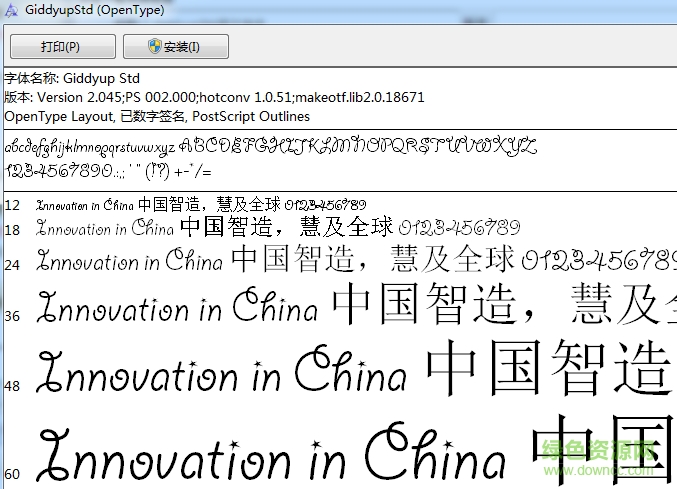
GiddyupStd字體是一款英文字體中的個(gè)性字體,字體的線條十分飄逸,真正做到了讓人過(guò)目難忘,這里擁有超多精彩的特殊字符寫法,有喜歡這一字體的朋友就趕快來(lái)綠色資源網(wǎng)下載使用吧!
GiddyupStd字體是一款個(gè)性英文字體,字體尤具個(gè)性的寫法,讓您的字能夠在眾多字體中脫穎而出,有需要的朋友就趕快來(lái)綠色資源網(wǎng)下載吧!